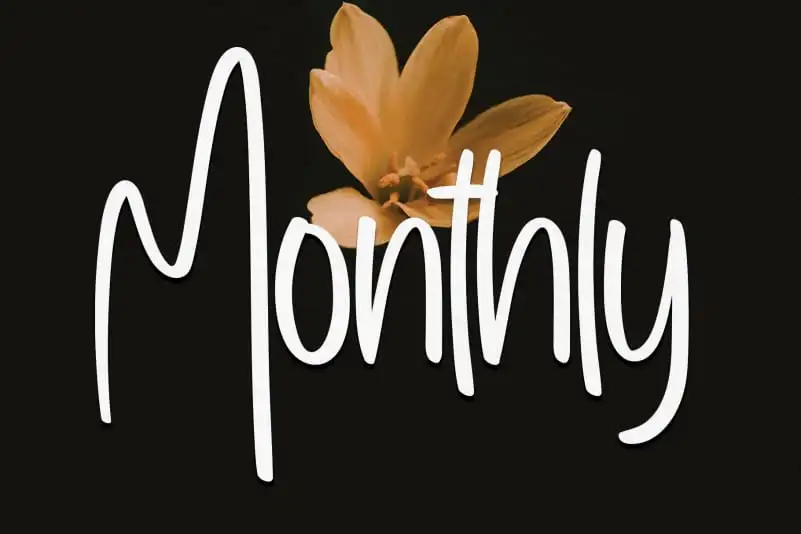
Monthly Script Font – Download Grátis
Na Monthly Script Font, criada pelo designer creativeletter, você encontra uma fonte escrita à mão que irá revolucionar a forma como visualiza e usa seu texto. Com linhas finas e suaves, essa fonte é perfeita para criar um toque delicado e elegante em qualquer projeto de design gráfico. A Monthly Script é ideal para incorporar elementos românticos e naturais em projetos relacionados à natureza ou a criação de mensagens pessoais. Seja para uma carta especial, anúncios de moda, ou até mesmo para adicionar um toque artesanal aos seus trabalhos online, essa fonte oferece um grau incrível de personalização e flexibilidade. Com sua aparência suave e fluida, a Monthly Script proporciona um acabamento delicado que combina perfeitamente com estilos mais elaborados e detalhados. Este não é apenas uma simples fonte, mas um elemento fundamental capaz de transformar qualquer design em algo único e emocionante. Experimente incorporá-la na sua próxima projeto para descobrir o verdadeiro potencial desta fonte escrita à mão. Crie mensagens que fluem com a mesma elegância da própria letra, criando uma conexão emocional direta com seu público.